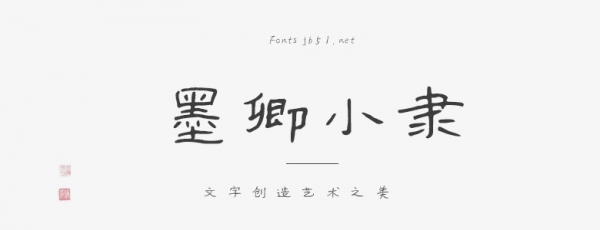
墨卿小隸是一款古色古香的手寫字體,橫筆造型多樣,字形較扁,結(jié)構(gòu)清晰,筆意精微,風(fēng)骨猶存,氣定神閑中透著靜謐靈動(dòng)。兼具欣賞和實(shí)用功能。適用于國(guó)潮經(jīng)典、傳統(tǒng)節(jié)日的主題排版,以及商業(yè)品牌的廣告設(shè)計(jì)。